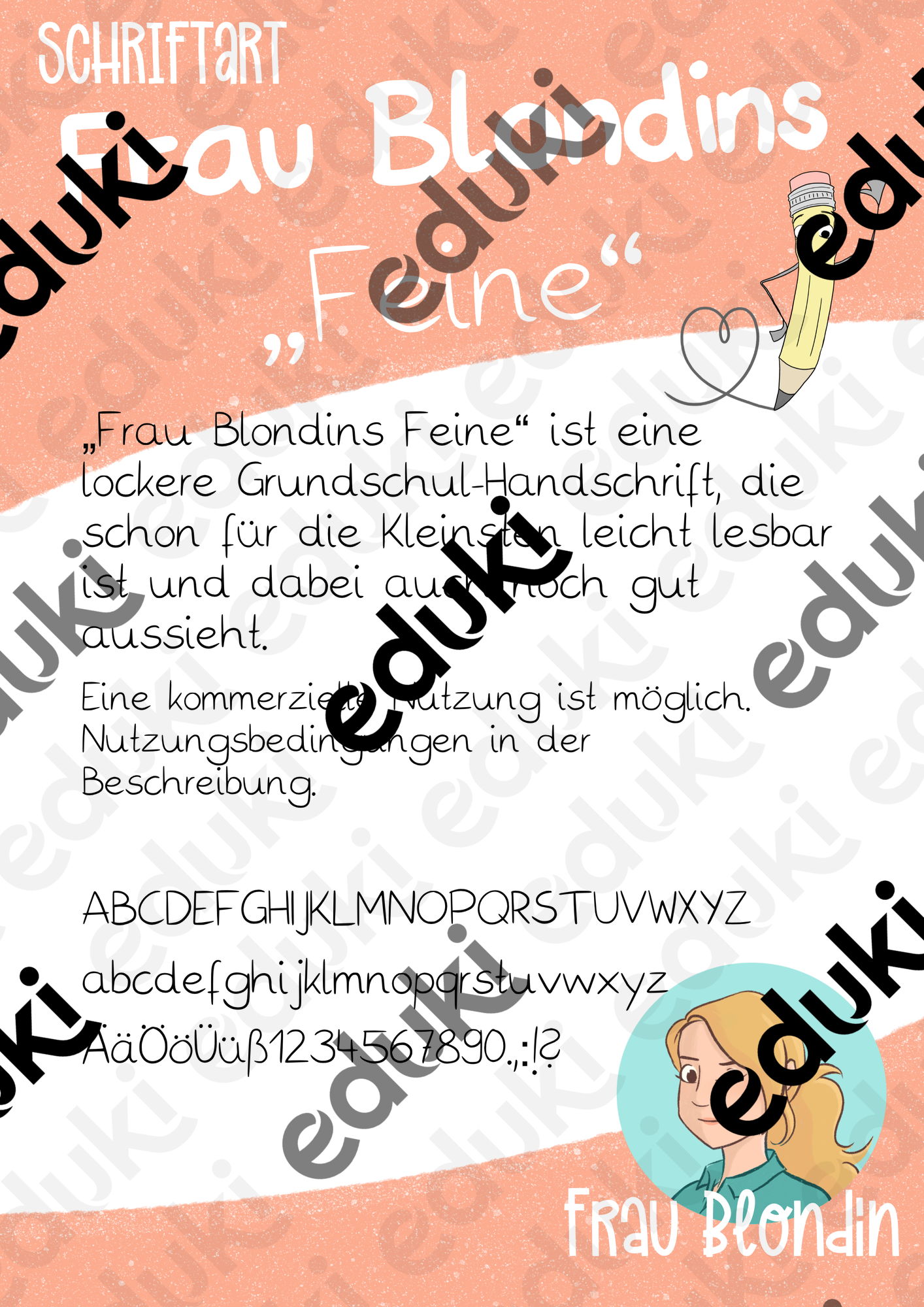
Dies ist eine von mir selbst erstellte Schriftart, die der Grundschrift ähnelt und schon von Kindern der ersten Klasse gut zu lesen ist.
"Die Feine" besteht aus eher fein geschriebenen Buchstaben. Meine Schriftart "Die Fette" bildet die perfekte Ergänzung dazu. "Die Fette" ist ebenfalls hier auf eduki.de erhältlich.
Die enthaltenen Buchstaben und Schriftzeichen sind auf dem Deckblatt angezeigt.